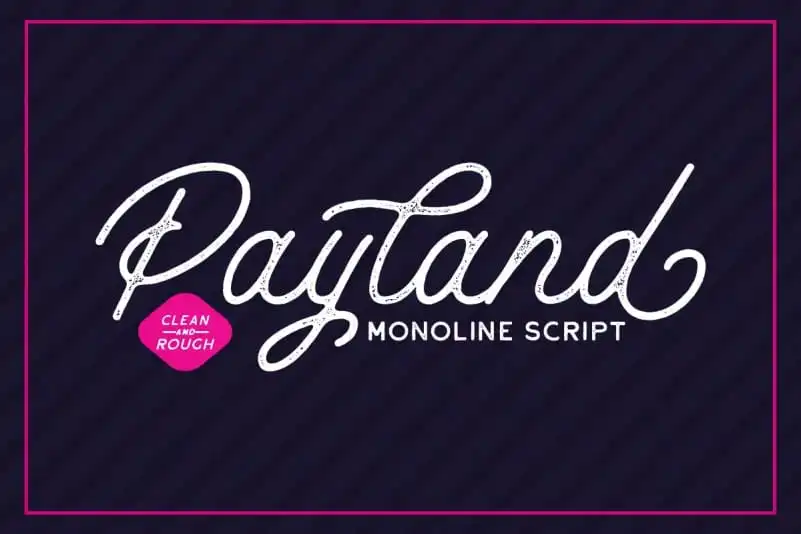
Descubra a magia de Payland Script Font, uma opção perfeita para quem deseja trazer sofisticação e elegância aos seus trabalhos digitais com um estilo script sofisticado. Este recurso especializado é ideal tanto para criações de logotipos quanto para texturas gráficas, oferecendo você a oportunidade de escolher entre uma versão limpa e simples ou uma opção mais vintage, dependendo do seu gosto pessoal. Com Payland, há sempre uma alternativa estilizada à sua disposição. Esta font contém um total de 11 alterações estilizadas, permitindo maior flexibilidade e criatividade no uso da fonte. Se você é fã de um design minimalista e limpo, não hesite em experimentar a versão regular; enquanto para quem procura algo mais vintage e artesanal, o estilo rough pode ser a escolha perfeita. Vivencie as curvas únicas e a inconfundível sensação de correnteza elegante que fazem desta font uma excelente opção para incorporar em seus projetos. Payland Script é um recurso de alta qualidade disponível na categoria de fonts script, projetada para ajudá-lo a expressar sua personalidade e criar designs únicos. O design da fonte foi criado por 99designs, um dos maiores mercados de criação de design no mundo. Se você está procurando por uma opção que combine sofisticação com facilidade de uso, Payland Script é o seu caminho.